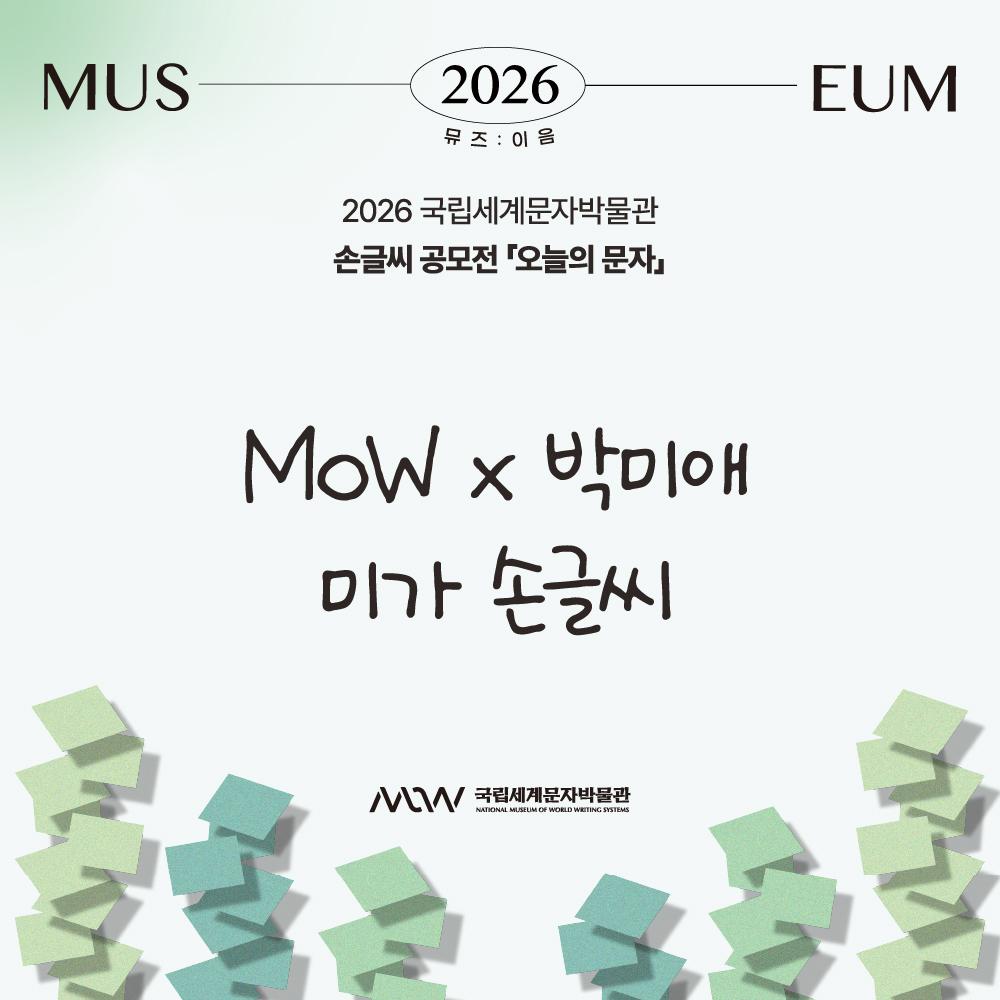
그리운 미가 손글씨
Griun MIGA Handwriting
그리운 미가 손글씨 소개
2026 국립세계문자박물관 손글씨 공모전 <오늘의 문자> 이 폰트는 2026 국립세계문자박물관 손글씨 공모전 <오늘의 문자> 수상자의 손글씨를 바탕으로 제작되었습니다. 수상자의 정갈하고 따뜻한 손글씨의 특징을 디지털 폰트에 담아, 손글씨만의 자연스러운 개성과 손으로 글씨를 쓰는 감성을 디지털 환경에서도 이어갈 수 있도록 구현했습니다.